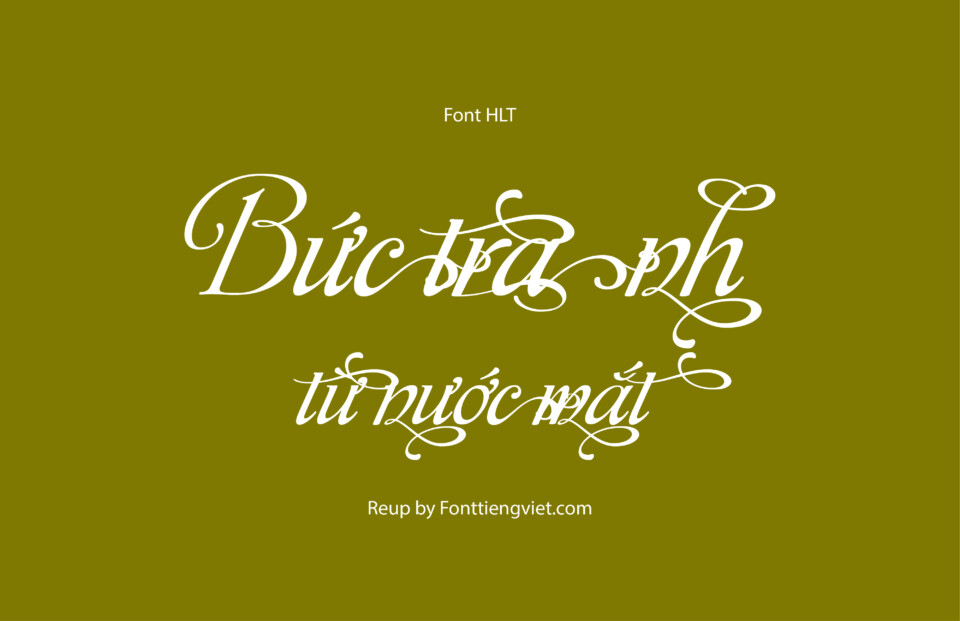
Font Việt hóa HLT Affair
Giới thiệu về Font Việt hóa HLT Affair
Font Việt hóa HLT Affair là một trong những bộ font chữ mang phong cách lãng mạn và tinh tế bậc nhất hiện nay. Được chuyển ngữ bởi cộng đồng HLT, bộ font này giúp người dùng dễ dàng gõ tiếng Việt có dấu mà không lo lỗi hiển thị. Trong lĩnh vực giáo dục và thiết kế học đường, việc tìm kiếm một Font Miễn Phí nhưng vẫn đảm bảo tính thẩm mỹ cao như HLT Affair là điều vô cùng cần thiết. Kiểu dáng của nó mang hơi hướng calligraphy hiện đại, với những đường nét uốn lượn mềm mại và bay bổng, tạo nên sự khác biệt hoàn toàn so với các phông chữ hệ thống khô khan thông thường.
Đặc điểm nổi bật của bộ chữ HLT Affair
Thiết kế thanh lịch và chuyên nghiệp
Đặc trưng của Font Việt hóa HLT Affair chính là sự kết hợp hoàn hảo giữa các nét thanh và nét đậm. Điều này giúp bộ chữ trở nên cực kỳ phù hợp cho các mẫu thiệp mời, bìa sách giáo khoa hay các dự án trình chiếu nghệ thuật. Bộ ký tự đi kèm được tối ưu hóa tốt, giúp các thầy cô giáo và học sinh dễ dàng tạo ra những sản phẩm đồ họa bắt mắt phục vụ cho việc giảng dạy và học tập.
Khả năng ứng dụng đa dạng
Bạn có thể sử dụng bộ font này trong nhiều phần mềm khác nhau từ Microsoft Office đến các công cụ thiết kế chuyên nghiệp như Canva hay Photoshop. Sự linh hoạt này giúp HLT Affair trở thành lựa chọn hàng đầu cho các bạn học sinh khi muốn trang trí slide thuyết trình hoặc làm báo tường điện tử độc đáo.